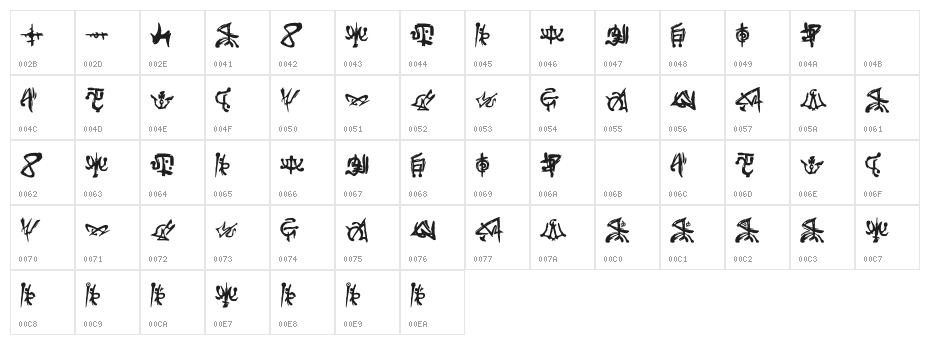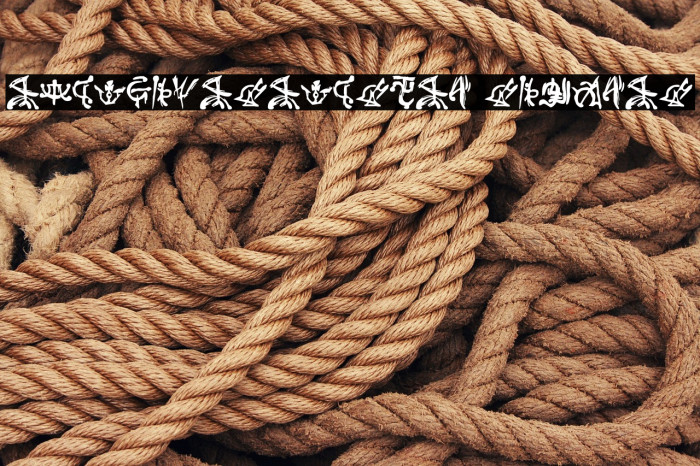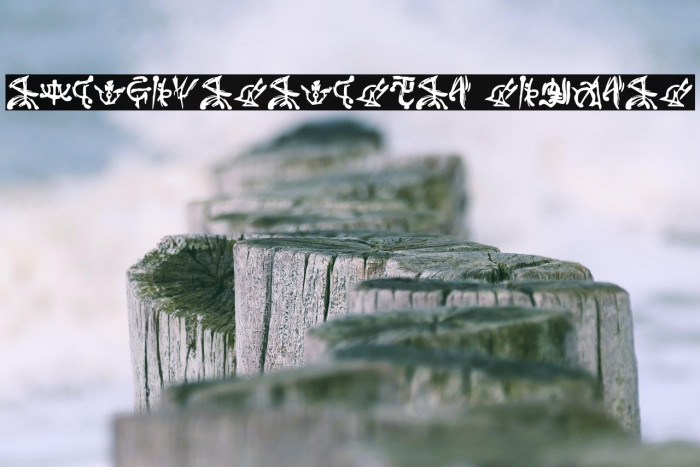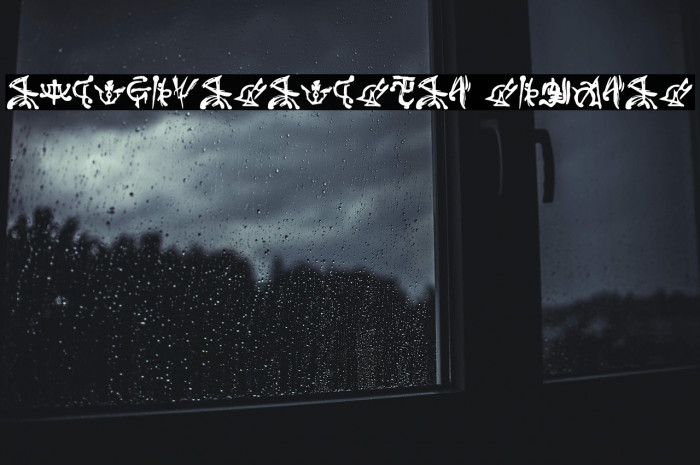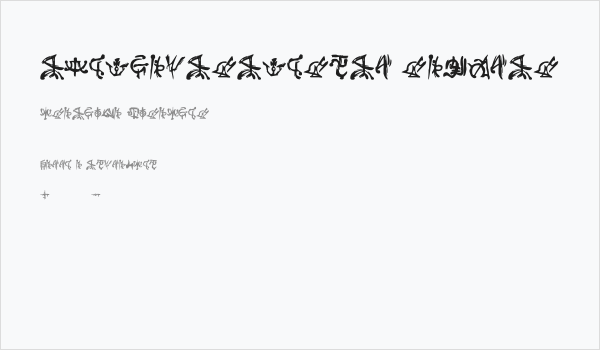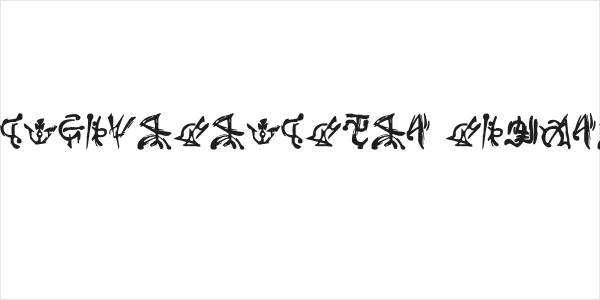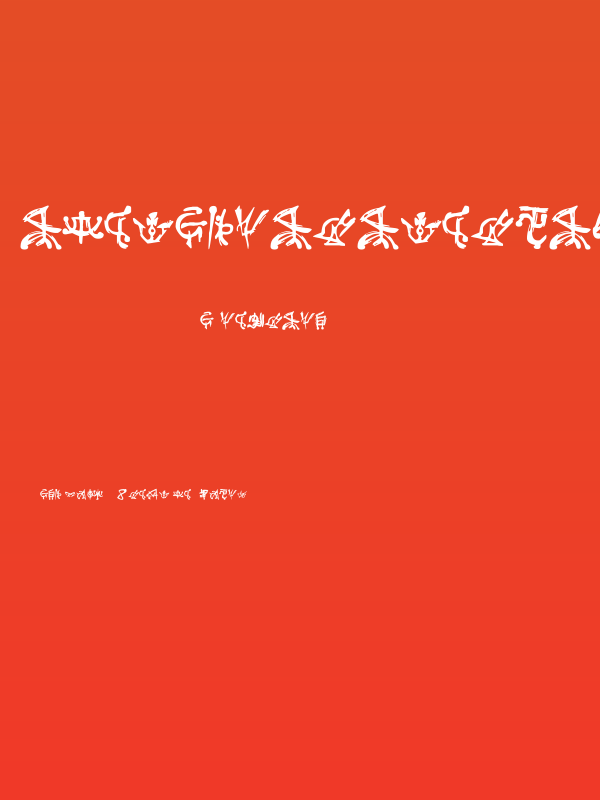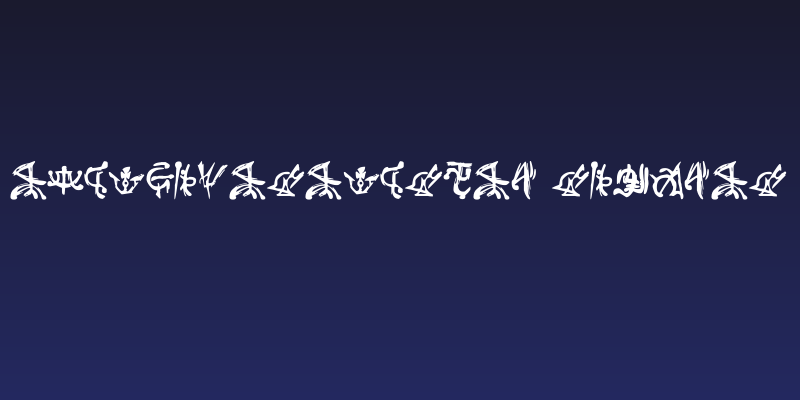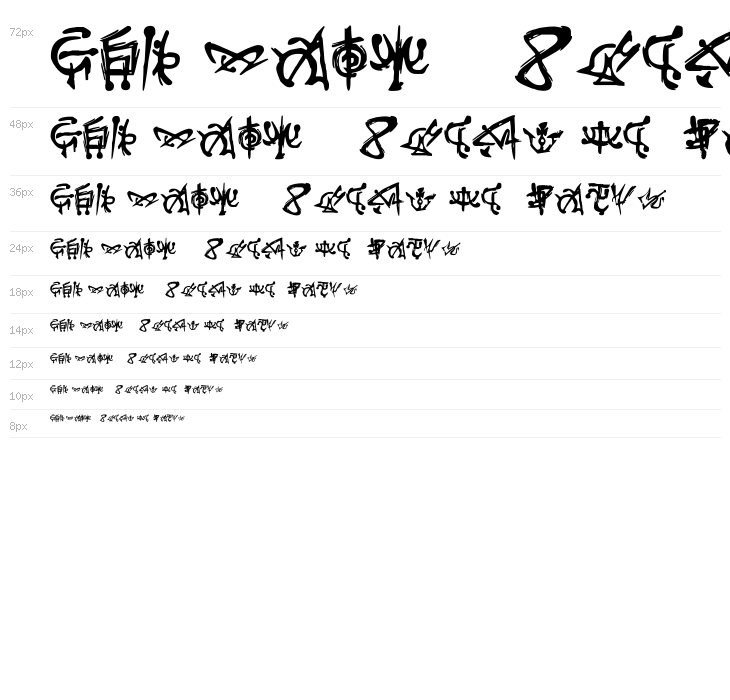
AFonteParanormal Regular Font
| Caz de utilizare | Logos, Posters, Artistic projects |
| Proiecte propuse | Ideal for fantasy-themed designs, book covers, movie posters, or any project requiring a mysterious and artistic touch. |